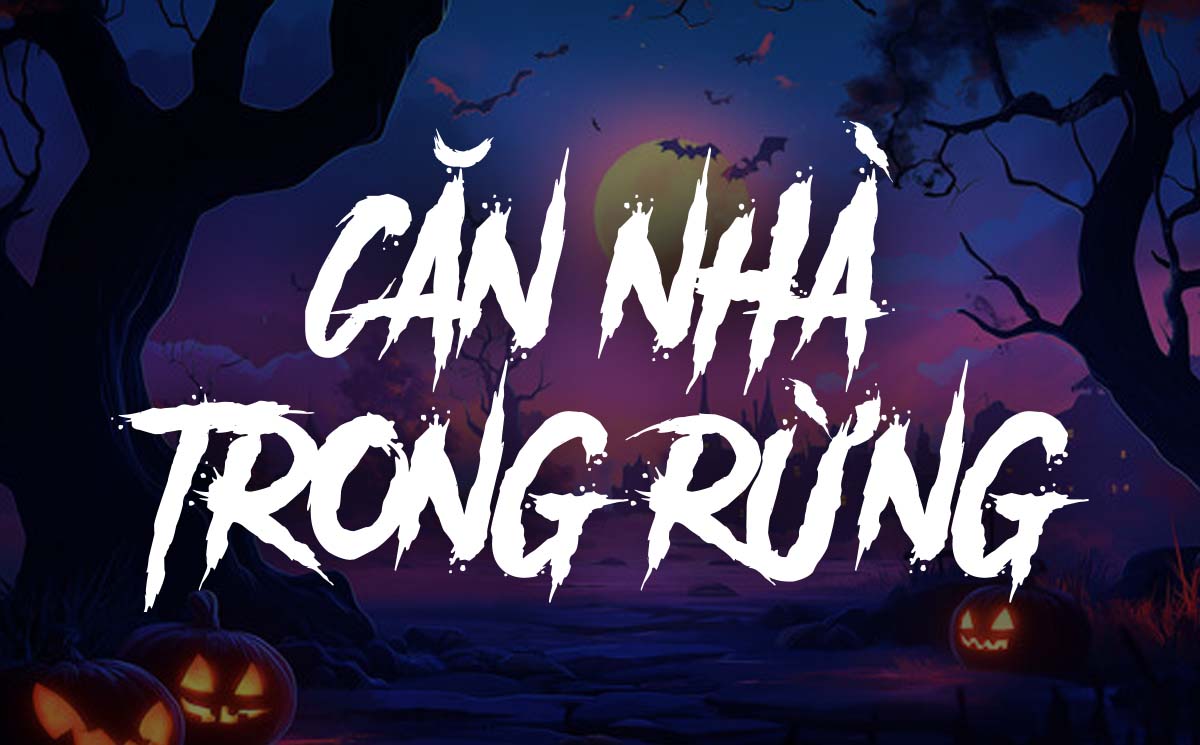
Giới thiệu font SVN Another Danger
SVN Another Danger là font chữ Brush với hiệu ứng nét cọ mạnh mẽ, được thiết kế theo phong cách kinh dị và bí ẩn. Những đường nét gồ ghề, phóng khoáng cùng cảm giác vẽ tay tự nhiên giúp font trở thành lựa chọn hoàn hảo cho các thiết kế mang chủ đề Halloween, phim kinh dị, lễ hội ma quái hay sự kiện giải trí.
Sau khi được Việt hóa đầy đủ, SVN Another Danger hỗ trợ hiển thị tiếng Việt đẹp mắt, giúp các designer dễ dàng sáng tạo mà vẫn giữ nguyên phong cách đặc trưng của font gốc.
Điểm nổi bật của SVN Another Danger
• Font Brush với hiệu ứng nét cọ mạnh mẽ, tự nhiên.
• Phong cách rùng rợn, gai góc, phù hợp chủ đề Halloween.
• Hỗ trợ đầy đủ dấu tiếng Việt sau khi Việt hóa.
• Thích hợp làm tiêu đề, poster, banner và thumbnail.
• Tạo điểm nhấn nổi bật cho các thiết kế mang phong cách kinh dị hoặc hành động.
Ứng dụng của font SVN Another Danger
Nhờ phong cách độc đáo, SVN Another Danger được sử dụng trong nhiều loại thiết kế sáng tạo như:
• Poster và banner Halloween.
• Thumbnail YouTube, Facebook Gaming.
• Thiết kế áo thun, sticker, decal.
• Logo cho sự kiện, lễ hội hoặc trò chơi kinh dị.
• Bìa sách, truyện tranh, phim kinh dị.
• Thiết kế quảng cáo theo phong cách grunge hoặc brush.
Khi kết hợp cùng các tông màu đen, đỏ, cam hoặc hiệu ứng máu, khói, font sẽ tạo nên bầu không khí huyền bí và đầy cuốn hút.
Vì sao nên chọn SVN Another Danger?
Nếu bạn đang tìm kiếm một font chữ mang đậm chất Halloween, SVN Another Danger là lựa chọn rất đáng cân nhắc. Font sở hữu các nét cọ thô ráp, không đều, tạo cảm giác chuyển động và mạnh mẽ, giúp tiêu đề nổi bật ngay từ cái nhìn đầu tiên.
Phiên bản Việt hóa giúp người dùng dễ dàng sử dụng trong các dự án tiếng Việt mà không gặp lỗi dấu, đồng thời vẫn giữ nguyên phong cách thiết kế của bản gốc.
Thông tin font
• Tên font: SVN Another Danger
• Phong cách: Brush
• Phân loại: Font nét cọ, Horror, Halloween
• Hỗ trợ: Tiếng Việt đầy đủ
• Ứng dụng: Poster, banner, logo, thumbnail, áo thun, sự kiện Halloween
Kết luận
SVN Another Danger là font Brush mang phong cách mạnh mẽ, gai góc và đậm chất Halloween. Với hiệu ứng nét cọ tự nhiên cùng khả năng hỗ trợ tiếng Việt đầy đủ, font là lựa chọn lý tưởng cho các thiết kế poster, banner, logo hay nội dung quảng bá theo chủ đề kinh dị. Nếu bạn muốn tạo nên những thiết kế ấn tượng, bí ẩn và khác biệt, SVN Another Danger chắc chắn là font chữ không nên bỏ qua.